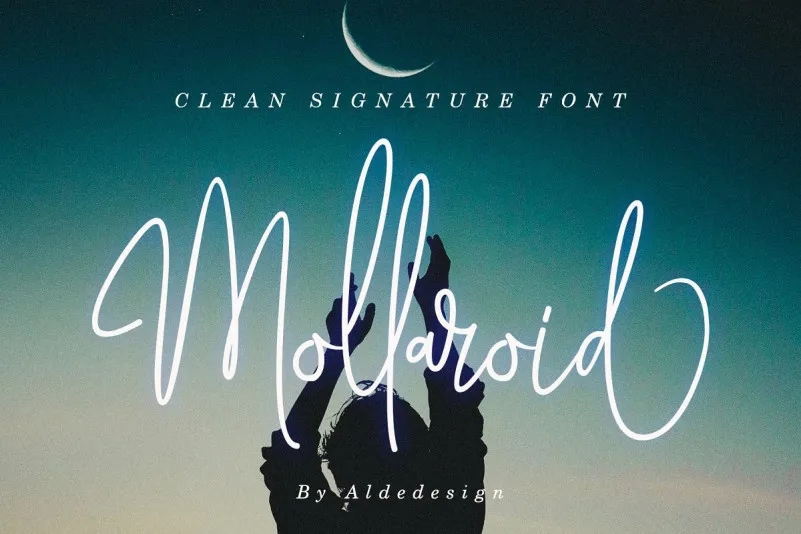
Mollaroid Signature Font – Download Grátis
Descubra a Mollaroid Signature Font para seu próximo projeto de design! Esta elegante tipografia de escrita manuscrita foi criada por Aldedesign e incorpora muitos ligantes, títulos e swashes que a tornam mais natural e autêntica. Com um estilo de firma, ela oferece uma maneira moderna e única de destacar seu trabalho. Esta fonte é perfeita para aquelas criações onde você quer transmitir sofisticação enquanto mantém-se em linha com o estilo manuscrito. Seja para nomes de empresa, selos de assinatura ou até mesmo cartões postais únicos, a Mollaroid Signature Font tem tudo para tornar seu design ainda mais impressionante e autêntico. Não perca tempo — instale-a já e deixe sua marca.